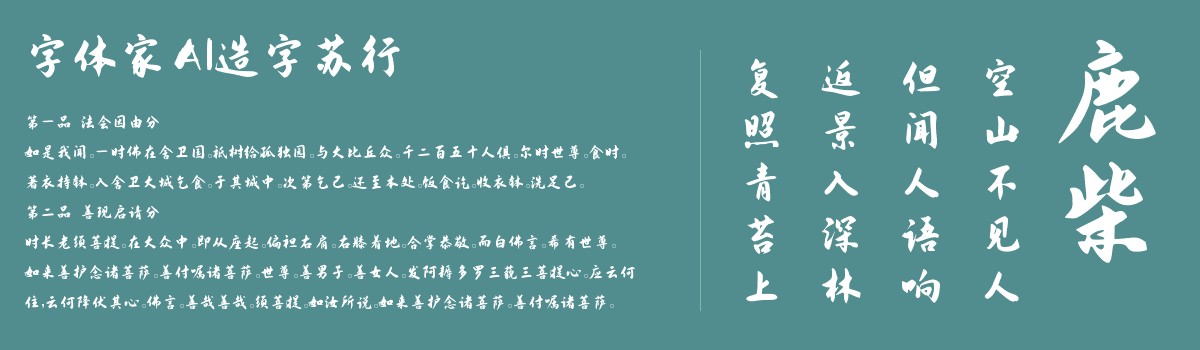
字体家AI造字苏行
字体家AI造字苏行是一款由字体家AI神笔造字生成的艺术字体,这款字体带着行书的灵动气韵,笔画如流水般连贯,起笔收笔温润不张扬,行笔时轻重有秩,像指尖轻划过宣纸的自然轨迹。转折处圆润带弹性,无生硬棱角,筋骨藏于流畅线条中。结构不呆板,略带舒展却稳当,似人闲坐时的从容姿态,既有手写的随性温度,又透着雅致的秩序感,触摸般能感知到笔触的轻重缓急与呼吸般的韵律。适合用于一些广告标题、平面文案、海报标题、网页广告用字的编辑。